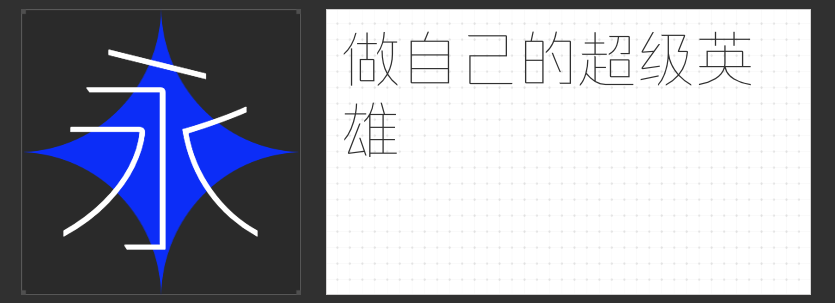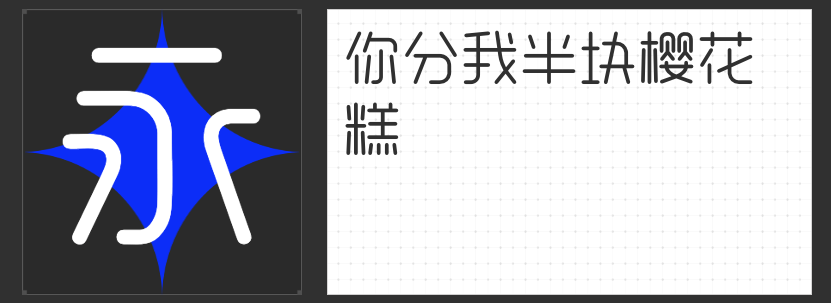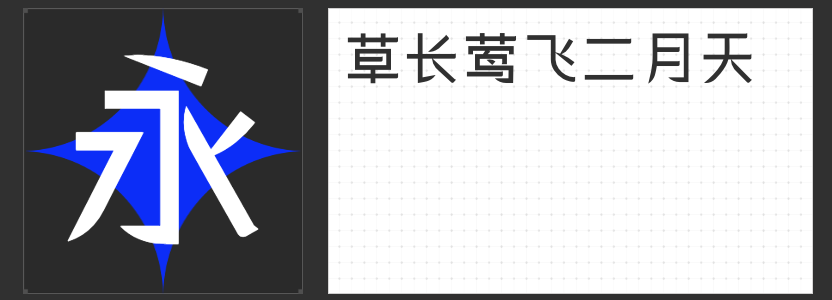
简约至美,形韵共生——四款现代极简风字体设计指南
在追求“少即是多”的极简主义设计中,字体不仅是信息传递的工具,更是构建视觉呼吸感的艺术元素。以下四款字体以克制的美学语言,将现代几何结构与东方留白哲学相融合,为UI界面、品牌标识、海报设计等场景提供兼具功能性与艺术性的解决方案。
一、励字超级勇士简 纤细
这款字体以建筑般的冷峻理性重塑黑体基因,45°斜切起笔赋予字形锐利的现代感,而笔画简省与极细字重的设计,让文字如玻璃幕墙般清透。斜切处理打破传统黑体的厚重感,在保持高辨识度的同时,释放出科技产品界面、时尚杂志排版所需的呼吸空间,完美诠释“轻盈力量感”的现代设计哲学。
二、创客贴幼稚园体细
当方正规整的几何造型遇上婴儿肌肤般的圆润笔触,这款字体创造出独特的治愈系美学。笔画终端的球形处理消解了直线的生硬感,如同孩童用蜡笔描绘的世界——既保留方形字体的稳定性,又以柔和边缘传递温暖童趣。适用于儿童教育品牌、生活美学周边等场景,让文字成为传递“天真力量”的视觉符号。
三、创客贴春晓宋常规
设计师以解构主义思维重塑宋体DNA,将书法飞白转化为几何留白,在笔画收尾处植入俏皮三角形切面。这款字体既传承了宋体横细竖粗的经典韵律,又通过模块化设计语言获得数字时代的适应性。方正骨架确保阅读舒适性,创意细节则赋予标题设计以艺术张力,特别适合文化类数字产品界面。
四、励字细圆简繁
作为无衬线体的终极演绎,这款字体以数学般的精确性构建视觉秩序。字面严格遵循黄金比例,笔画粗细误差控制在0.1mm以内,横竖笔画的绝对均质化处理,创造出类似精密仪器的冰冷美感。摒弃一切装饰性元素,却通过笔形微调确保文字在极小字号下的清晰度,是金融平台数据可视化、科技峰会主视觉的理性之选。
从锐利的几何切割到温润的有机形态,这四款字体构建了极简设计的多维光谱。它们用克制诠释丰富,以规则拥抱自由,既满足现代设计对功能性的严苛要求,又为数字化表达注入人文温度。当信息洪流裹挟时代,或许正是这些静默的文字,在屏幕与纸张间筑起抵御喧嚣的视觉净土。